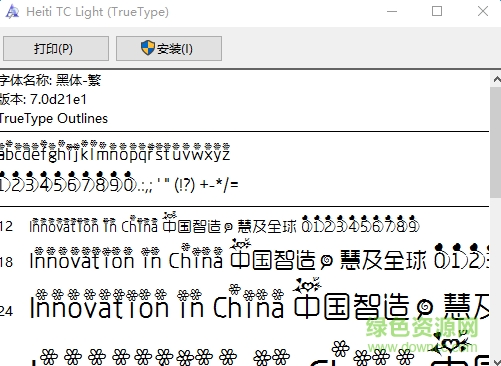
戀愛(ài)城堡
戀愛(ài)城堡字體是一款很甜蜜的電腦藝術(shù)字體,就像它的名字所說(shuō)那樣是一款充滿了戀愛(ài)味道的字體,寫(xiě)出來(lái)的字也是超級(jí)好看的,用來(lái)藝術(shù)寫(xiě)作應(yīng)該會(huì)很好看吧,歡迎大家來(lái)綠色資源網(wǎng)下載。
戀愛(ài)城堡字體
戀愛(ài)城堡字體字形非常有特色,寫(xiě)出來(lái)的字當(dāng)然也就很有個(gè)性了,使用范圍也很廣,藝術(shù)設(shè)計(jì)、廣告設(shè)計(jì)都是可以的,喜歡的朋友就快來(lái)綠色資源網(wǎng)下載吧。